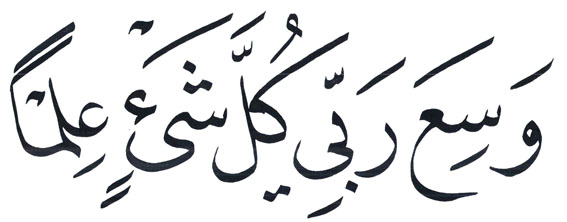
خط النسخ العادي والمشكل القديم والحديث
يعود الفضل إلى الخطاط ابن مقلة الشیرازی في تأسيس وإبداع خط النسخ
وذلك في أوائل القرن الرابع الهجري/أواخر القرن التاسع الميلادي .
وقد ساهم في تطويره وتنويعه بعد ذلك العديد من الخطاطين الأتراك والعرب منذ بداية تأسيسه وحتى عصرنا الحالي .
وسمي خط النسخ بذلك الاسم لسهولته ولكثرة الكتابه به ونسخ المقالات والكتب القديمه به
وما زال خط النسخ حتى وقتنا الحالي هو أكثر الخطوط العربيه استخداماً
حيث يتم الكتابه به في الكتب والمجلات والصحف ومواقع الانترنت
وأنظمة تشغيل الكمبيوتر والجوالات والأجهزه اللوحيه
فهو الخط الأكثر انتشاراً ويكفي أن نقول أنه قد تم نسخ وكتابة القرآن الكريم بهذا الخط الرائع والمميز حقاً .الخط يدعم جميع برامج شركة أدوبي ومايكروسوفت أوفيس وكوريل درو